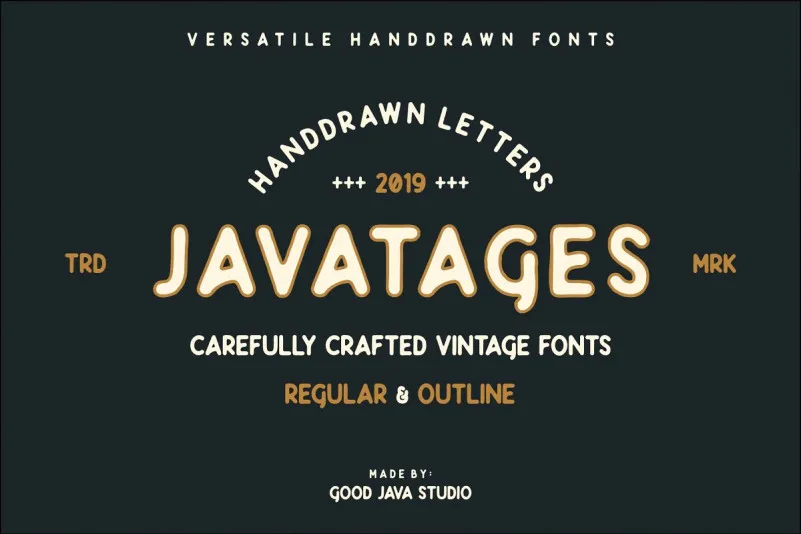
Javatages Bold Vintage Font – Download Grátis
Esta é uma fonte tipográfica em estilo script com destaque sóbrio, mas casual. Ela foi criada pelo Good Java Studio inspirada no estilo vintage e compartilhada pela f0rdesigner, que introduz a font Javatages. Este tipo de letra faz um giro interessante do que vemos nas demais fontes vintage, com várias configurações estilizadas de ângulos diferentes. É perfeitamente adequada para projetos como logotipos, tipografia, marca, etiquetas e embalagens ou qualquer projeto gráfico em busca de um toque de estilo vintage.